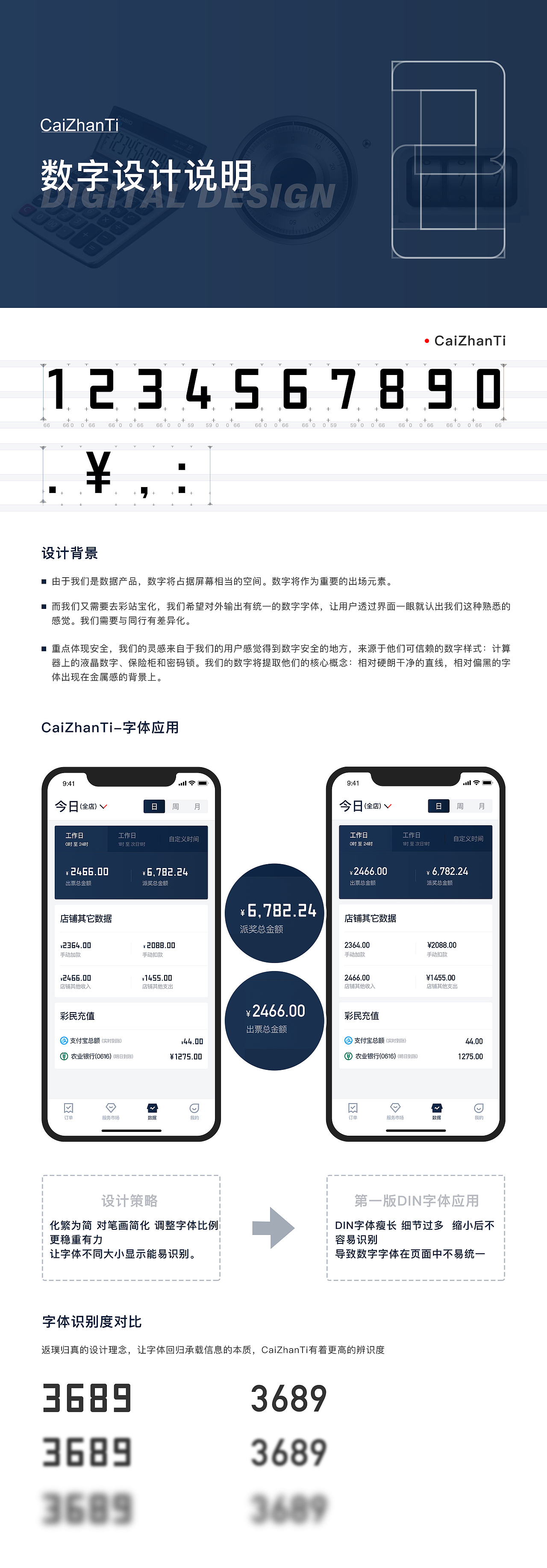
CaiZhanTi-字体设计
1、B端数字字体设计,由于我们B端产品线,数据作为重要的出场元素。
2、我们需要去品牌化,希望对外输出有统一的数字字体,为用户灌输品牌意识,同时我们需要与同行有差异化。
3、字体设计来源于他们可信赖的数字样式:计算器上的液晶数字、保险柜和密码锁。我们的数字将提取他们的核心概念:相对硬朗。 干净的直线,相对偏黑的字体出现在金属感的背景上。
4、安全感是与生俱来的本能需求,财务工具安全感更加是第一需求。我们立求提供本能的安全感。